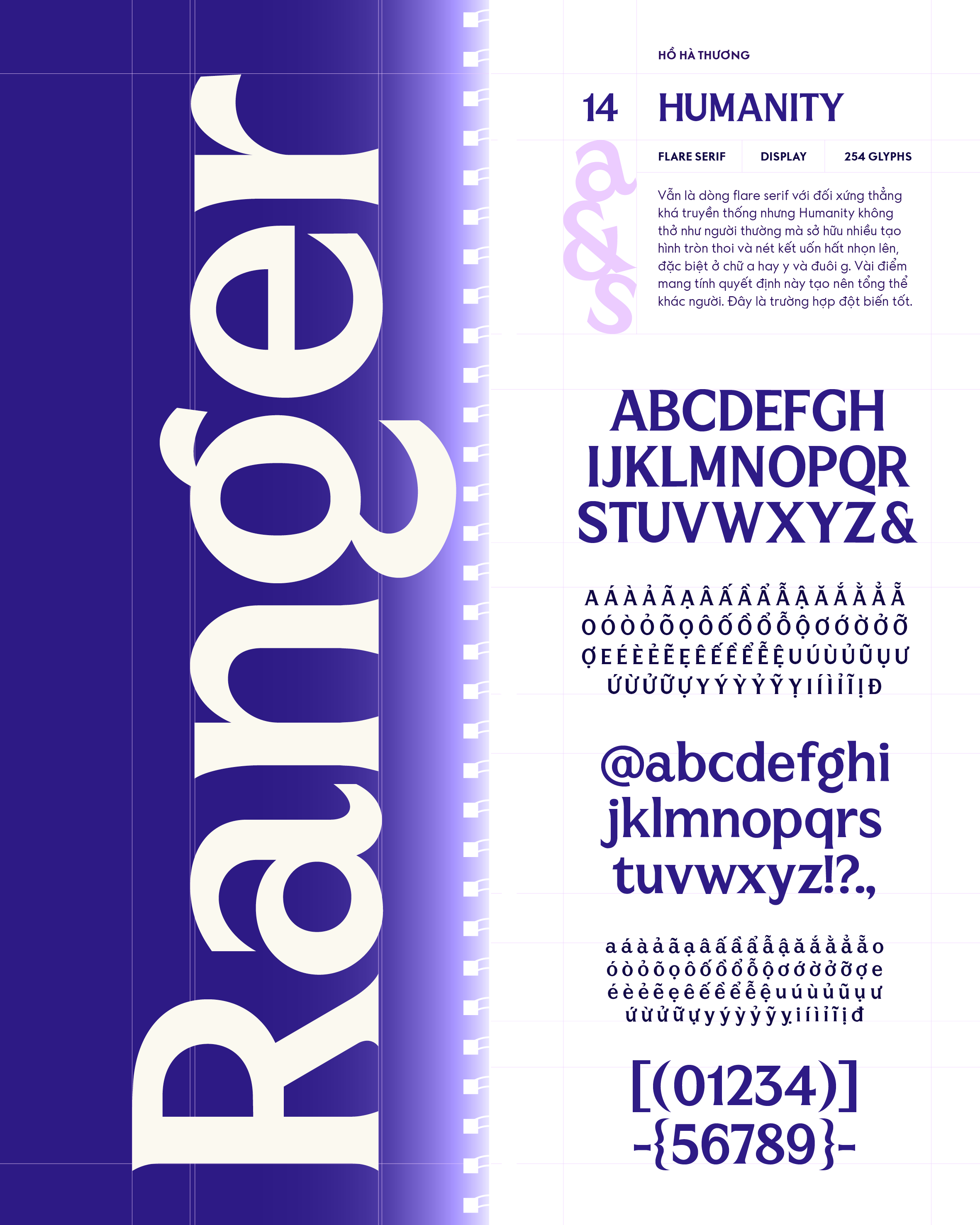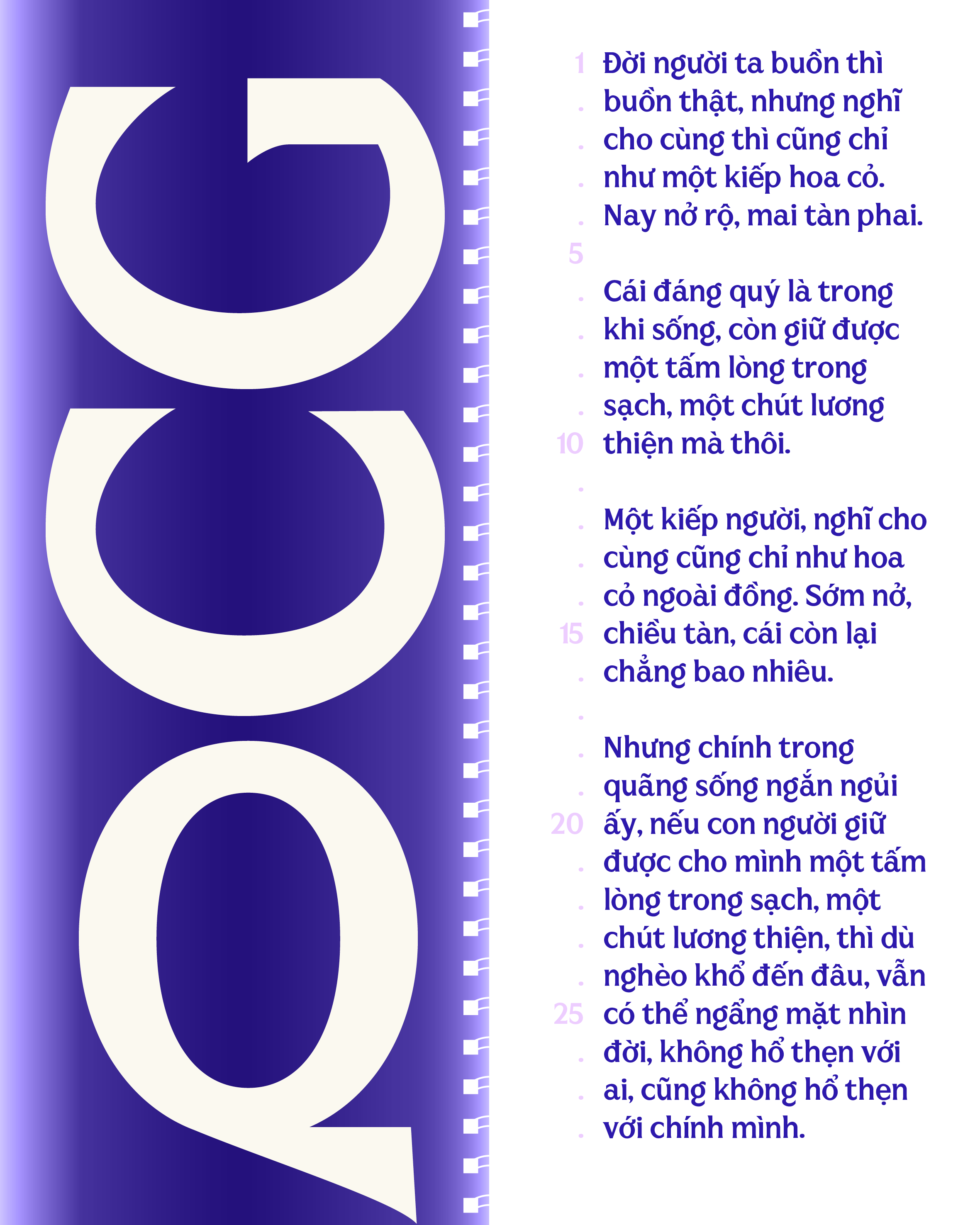
Humanity
Về Humanity: Vẫn là dòng flare serif với đối xứng thẳng khá truyền thống nhưng Humanity không thở như người thường mà sở hữu nhiều tạo hình tròn thoi và nét kết uốn hất nhọn lên, đặc biệt ở chữ a hay y và đuôi g. Vài điểm mang tính quyết định này tạo nên tổng thể khác người. Đây là trường hợp đột biến tốt.
Flare serif
Display
Hồ Hà Thương
Humanity
NeoCity 127
Humanity
Hundred Lies
Humanity
Lương thiện
Humanity
Sớm nở chóng tàn
Humanity
Một kiếp người, nghĩ cho cùng cũng chỉ như hoa cỏ ngoài đồng. Sớm nở, chiều tàn, cái còn lại chẳng bao nhiêu.
Humanity
Nhưng chính trong quãng sống ngắn ngủi ấy, nếu con người giữ được cho mình một tấm lòng trong sạch, một chút lương thiện, thì dù nghèo khổ đến đâu, vẫn có thể ngẩng mặt nhìn đời, không hổ thẹn với ai, cũng không hổ thẹn với chính mình.